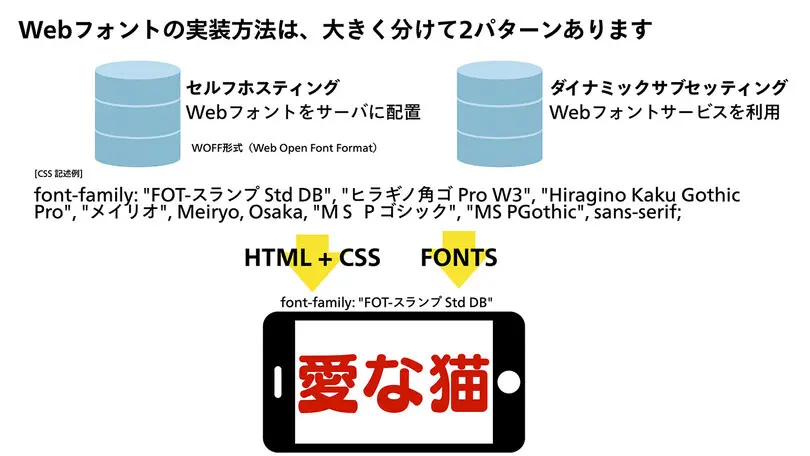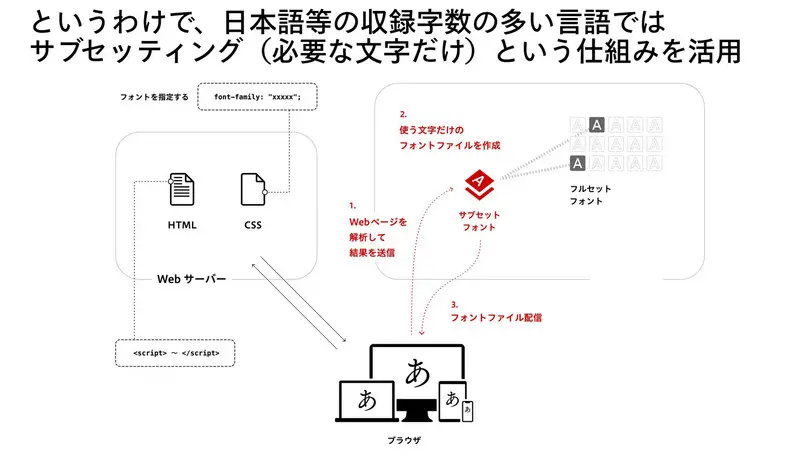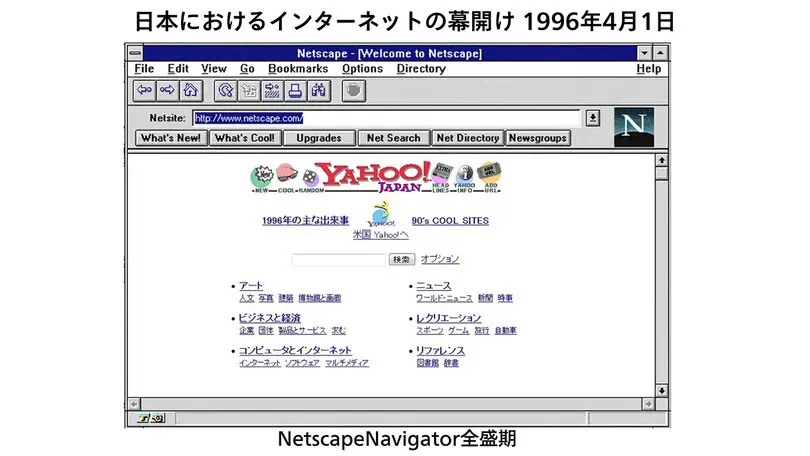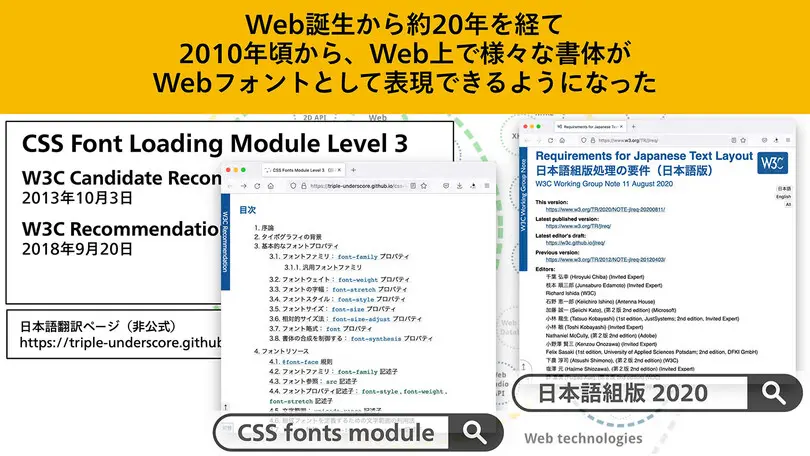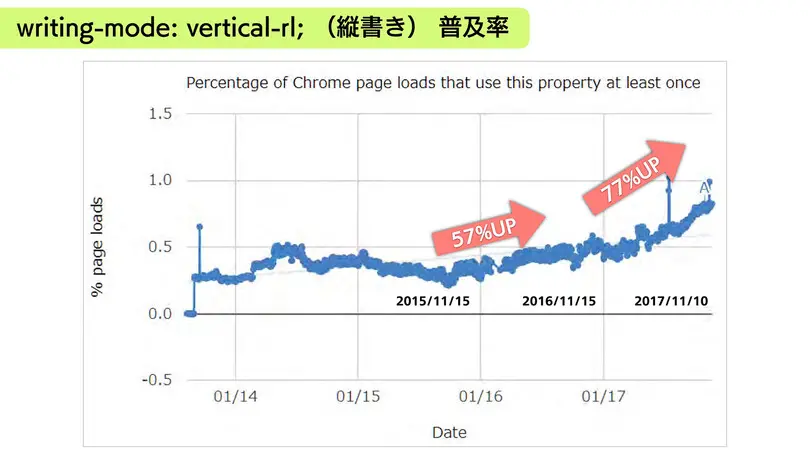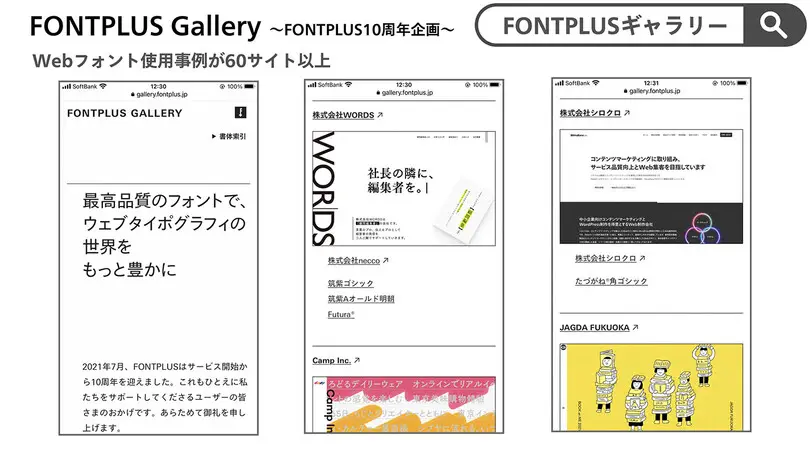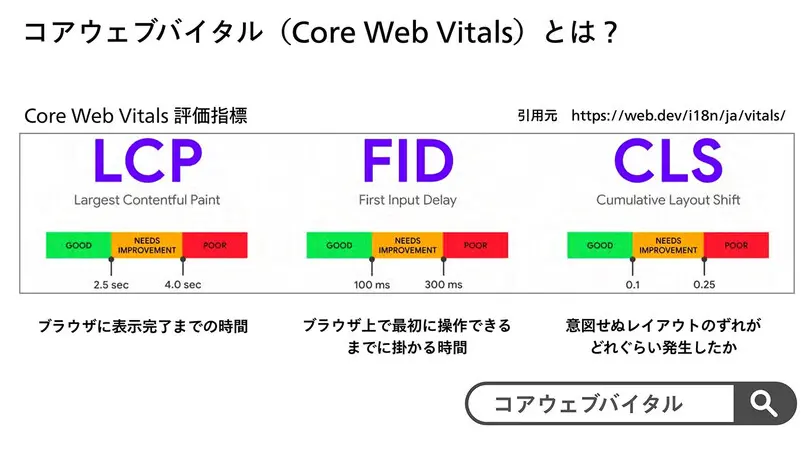
日本語Webフォントの課題と解決策
フォントおじさんこと関口浩之氏によるプレゼンテーション。ブランディング、アクセシビリティ、デザイン性の向上などを実現する手法として重要な役割を果たすWebフォント。基本的な疑問にテクニカルな視点で徹底解説。Webフォント導入事例を紹介しながら、オンスクリーンタイポグラフィは、2021年はどこまで進化したのかなどお話しします。
関口氏は、幼い頃から琺瑯(ほうろう)看板の手書き文字に魅せられ、80年代、プリンターやワープロを扱う電機メーカーに在籍したのち、1995年よりソフトバンク技研(現SBテクノロジー)に入社。2011年9月に日本語Webフォントを扱うサービス「Fontplus」を開始しました。現在では日本やアジア圏のフォントメーカー14社の3500書体が使えるWebフォントのプラットフォームに成長。2017年ごろから「フォントおじさん」と呼ばれるようになり、文字の伝道師(エバンジェリスト)として、「Fontplus Day」というコミュニティも運営しています。
このセッションでは、日本語Webフォントの課題を技術的な観点からQ&A形式で楽しく解説していただきました。
Q1:日本語Webフォントが誕生して約10年。当時の日本語Webフォントってどんな感じでしたか?
A:10年前の日本語Webフォントの表示速度は遅く、サイトにアクセスすると最初にシステムフォントが出て、5秒後ぐらいにWebフォントに置き換わっていました。2013年からWebフォントの配信側の速度が改善し、1秒くらいで表示できるようになりました。
Q2:日本語Webフォントの仕組みをわかりやすく解説してください。
A:Webフォントの実装方法は、大きく分けて二つあります。一つは「セルフホスティング」。自分たちのサーバーにWebフォントを配置する方法です。もう一つは、「ダイナミックサブセッティング」。表示に必要な文字のデータだけをWebフォントサービスのサーバーに取りに行って表示させる方法です。
例えば、
font-family: “FOT-スランプ Std DB” “ヒラギノ角ゴ Pro W3” “ Hiragino Kaku Gothic Pro” “メイリオ”, Meiryo, Osaka, “MS P gosikku“, “MS P Gothic”, sans-serif;
というCSSの場合、先頭からそのフォントがあるかどうかを見ていき、あった場合はそのフォントが表示され、なかったら次のフォントが表示されます。
中国語、日本語、韓国語など収録字数の多い言語では、このサブセッティング方式を活用。フォントに含まれている全データを取ってくるのではなく、表示されている必要な文字データのみを取ってきて表示するのです。
現在、日本語に対応しているWebフォントサービスには以下があります。
• Fontplus
• TypeSquare
• DynaFont
• Realtype
• FontSream
• Adobe Fonts
• Google Fonts
Q3:10年前からWebフォントが注目されるようになったのはなぜ?
A:30年前のネット黎明期から説明しましょう。イギリス人のティム・バーナーズ=リー博士がWorld Wide Web(WWW)を1990年に考案。1994年、マサチューセッツ工科大学に着任した直後、World Wide Web Consortium(W3C)を設立。WWWの仕様や指針、標準技術を策定、開発しました。それから今日に至るまで、W3Cが中心となり、Web標準化を継続的にアップデートしてきたことにより、現在のWebタイポグラフィが実現したのです。
日本では1996年4月1日、Yahoo! Japanによって、いつでも誰でもどこからでもインターネットで検索できるようになりました。当時はWindows95/漢字Talkの時代で、搭載フォントも少なく、Webサイトでは見出しなどの文字を画像にして表現していました。その後、W3Cがいろいろな仕様を定義し、Webフォントが使えるようになりました。つまり、Webの誕生から約20年を経た2010年ごろから、Web上で様々な書体をWebフォントとして表現できるようになったのです。
W3Cの提案を受け、各ブラウザメーカーは実装に向けて努力をしています。Web技術は日々進化しているので、最新技術をキャッチアップしておきましょう。
Q4:Webブラウザで縦書き表現はできるのでしょうか? さらに、縦書き横書き混在レイアウトはできるのでしょうか?
A:できます。以下は縦書きを使ったサイトの一例です。
宮城県丸森町のWebサイト「まるまるまるもり
鈴乃屋「衣のいのち
writing-mode: vertical-rl;
縦書き普及率のグラフ。2017年には縦書きが77%増加。
Q5:最近リニューアルした案件で、おすすめの事例を教えてください。
A:Webフォントの使い方が上手な事例をいくつか紹介します。
株式会社WORDS
言葉のプロ、伝えるプロとして編集者が企業経営者の発信をサポートする株式会社WORDSのWebサイト。「社長の隣に、編集者を。」というキャッチコピーは、アンチゴチ(漢字がゴシック、仮名が明朝で組まれた、漫画の吹き出しなどで使われているスタイル)ではなく、漢字が明朝(筑紫Aオールド明朝)、仮名がゴシックで組まれている。書体の選定やレイアウトも素晴らしく、表示速度も速い。
レタースペーシング
今市達也さんが執筆した書籍『レタースペーシング』のWebサイト。たづがね角ゴシックを使用し、文字間調整もきちんと行われている。Webフォントに切り替わる時のチラつきもなく、高い技術力を感じる。
Q6:日本語Webフォント導入事例をもっと知りたい。
A: いくつか事例を紹介します。
東京都現代美術館
美術館内の案内表示で使われている、たづがね角ゴシックのWebフォントをサイトでも使用。
SUN-AD サン・アド
ナビゲーションが縦組みで配置されているが違和感がなく、こぶりなゴシックの雰囲気とも調和している。
そのほかの事例は、「Fontplusギャラリー」参照。
Q7:Webフォントを導入するとコアWebバイタル(コアウェブバイタル)の評価に悪影響を与えるのでしょうか?
A:Googleが導入したWebの指標
・LCP(Largest Contentful Paint)ブラウザに表示完了するまでの時間
・FID(First Input Delay)ブラウザ上で最初に操作できるまでにかかる時間
・CLS(Comulative Layout Shift)意図せぬレイアウトのズレがどれだけ起こるか
コアウェブバイタルの測定結果が「Good」だからSEO的によいというものではありません。悪影響を与える場合もあれば、そうでない場合もあります。表示パフォーマンスが悪い場合、何が原因なのか冷静に正しく判断しましょう。Webフォントが原因でない場合もあります。
「Web Vitals」というプラグインを入れて、実際にサイト表示にかかる時間(LCP)を調べてみました。この旅日記のブログでは0.81秒。全部Webフォントを使っているサイトでも、「Good」という結果が出ています。「表示が遅い」というサイトを調べてみると、約9割はWebフォント以外の要因が原因でした。Webフォントを使うと表示が遅くなるということはないと思います。
Q8:Webフォントってアクセシビリティ的にどうなの?
A:文字情報を画像データとして表現した場合、テキスト情報を代替テキスト(alt属性)にすべて記入します。Webフォントやシステムフォントであれば、代替テキストを記述する必要はありません。
Q9:日本語Webフォントは流行っているの?
A:2017年に企業のWebサイトでWebフォントがどのくらい使われているのかを調べたところ、海外のFortune500企業では95%以上が自社サイトにWebフォントを採用。日本の日経500企業では5%でした。
日本語と欧文言語では文字数が全然違います。欧文は1書体600文字で間に合いますが、日本語は1書体6000〜23000文字あります。2016年まで日本語Webフォントは苦戦していましたが、Windowsでの閲覧環境が改善されたため、その後、普及してきています。
日本語Webフォントが誕生して10年。2017年から日本語Webフォントを取り巻く環境は改善し、大手企業やWeb制作の現場から市民権を得ています。
Q10:おすすめの書体(Webフォント)を教えてください。
A:このフォントを使えば大丈夫というフォントはありません。その企業のビジョンやブランド、サイト適性やコンテンツに応じて適材適所の書体選択が重要です。
Context(文脈)× Fonts(書体)
(Fontplusを利用している3万サイトで使われている書体を調査し、使用頻度順に並べたもの)
1位:筑紫ゴシック
2位:筑紫A丸ゴシック
3位:筑紫明朝
Q11:Webデザインはグラフィックデザインに追いつくことができたの?
A:グラフィックとかWebの垣根がなくなってきています。見る側は、紙/Webの媒体を意識していません。いかに情報を正確に伝えるのか、そのもとになっているのがフォントだと思います。Webフォントとは、情報を正確に伝えるためのコミュニケーション基盤なのです。
質疑応答
Q:Webフォントで容量が軽いものは?
A:フォントの容量は、線の複雑さによって変わってくるので、明朝体に比べるとゴシック体の方が数割軽いというのはあるかもしれません。Webサイトに8000字くらいの長いテキストがあったとしても、平仮名は重複しているので、大体600文字くらいです。したがって、容量は100キロバイト、200キロバイトと軽くなります。サブセット化してくれるWebフォントサービスを使うと軽量化できると思います。
Q:Webフォント技術が発達していく中で、今ゴール地点を決めるとしたら、どこが目標になるのでしょう?
A:Webフォントを提供する側としては、サブセッティングは必須の技術です。最初のページを読み込んだ後、次のページを読み込むときに、その差分(まだ読み込んでいない文字)をブラウザ側で解析して、差分の文字だけを取りにいくような技術がWeb標準技術として実装される時代が来ると思います。それがある意味、現時点でのゴールになる感じがします。
Q:ユーザー側の好みによって、Webフォントのサーバー側で判断して表示を微調整できるようなサービスはあるのでしょうか?
A:ブラウザの行送り値によって、行送りを変えて表示する技術はすでにあります。技術が普及するとWebに実装され、標準化されていくのですが、それまではサービス側で提供して課題を解決することになりますね。